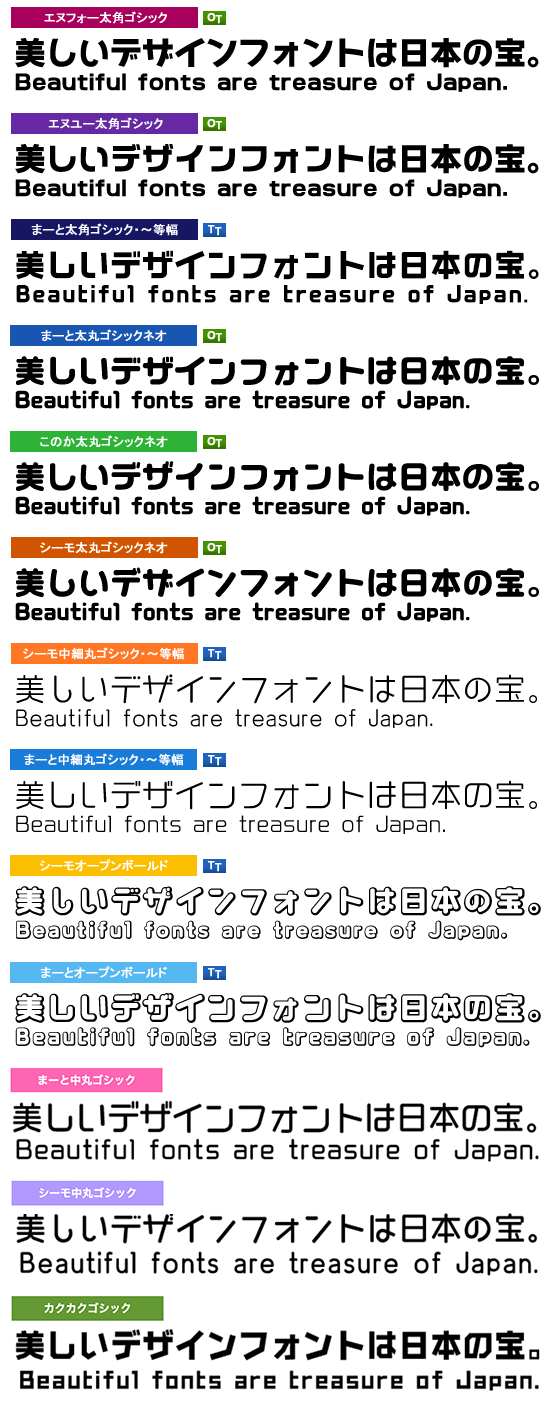
CFONT日本語13書体特別セット
CFONTブランドの 日本語書体 (漢字入り書体) 全13商品 をひとまとめにした特別セット。
収録文字数(JIS第一水準、第二水準6355文字、ひらがな、カタカナ、約物記号、アルファベット等647文字)
CFONTの紹介
CFONTは下島正人氏が手掛けるフォントライブラリー。キャッチコピーやタイトルを目的としたディスプレイタイプフォントを制作しており、個性的なフォルムを重視しながらも可読性も考慮されたデザインが特徴です。